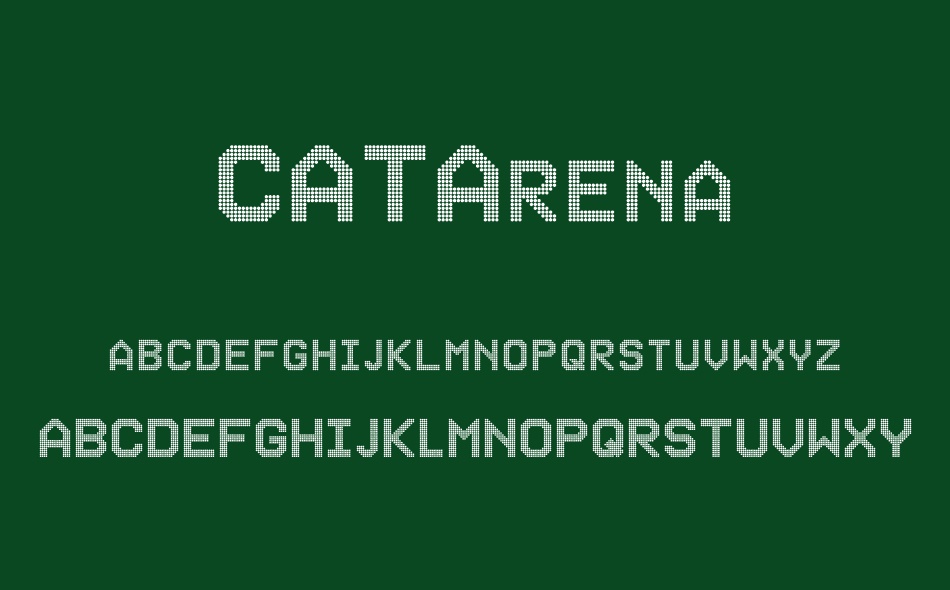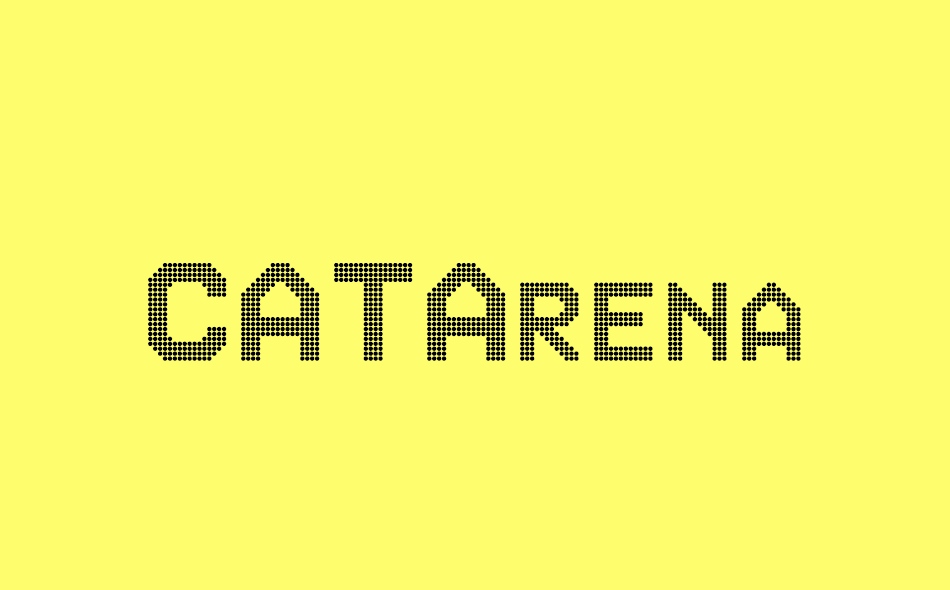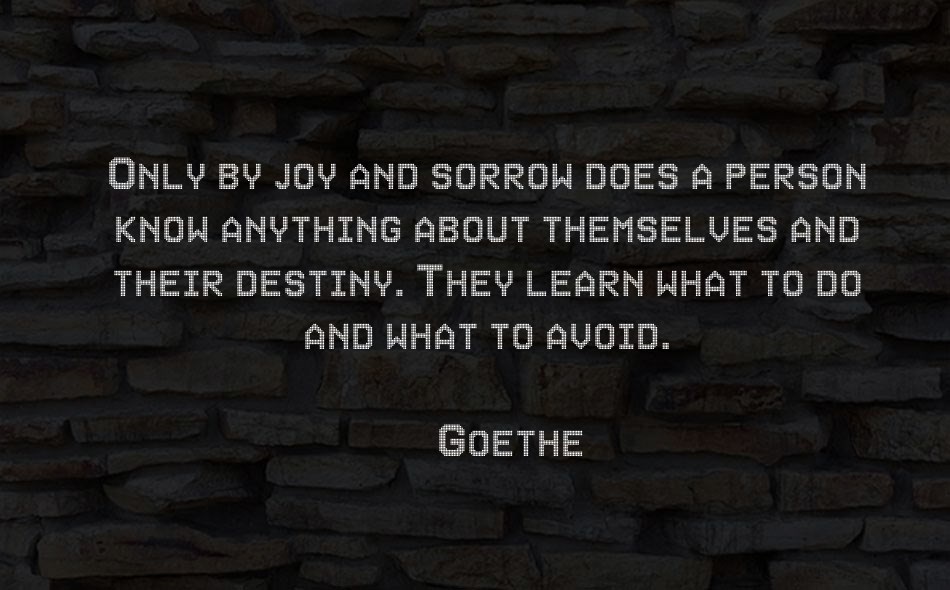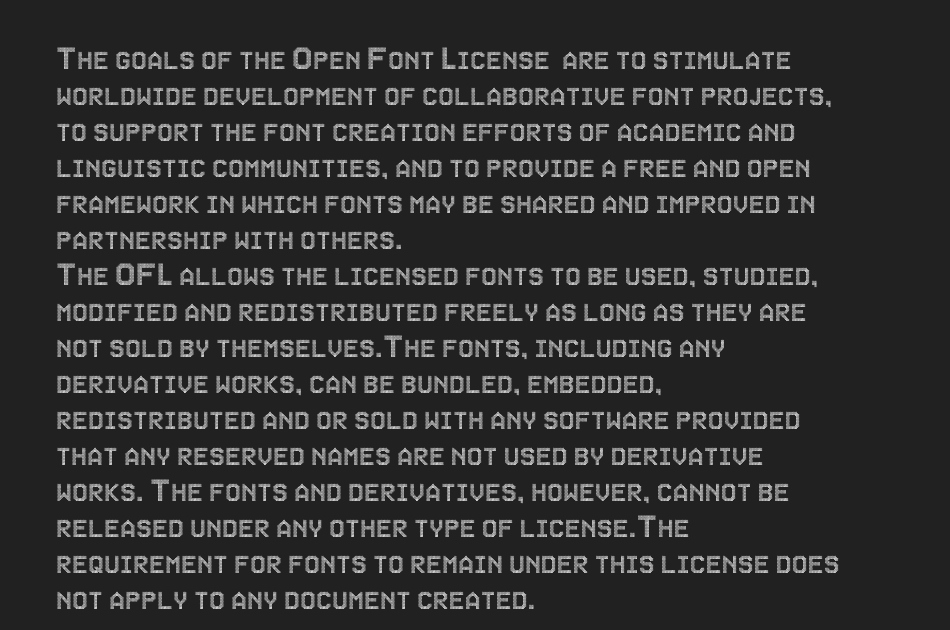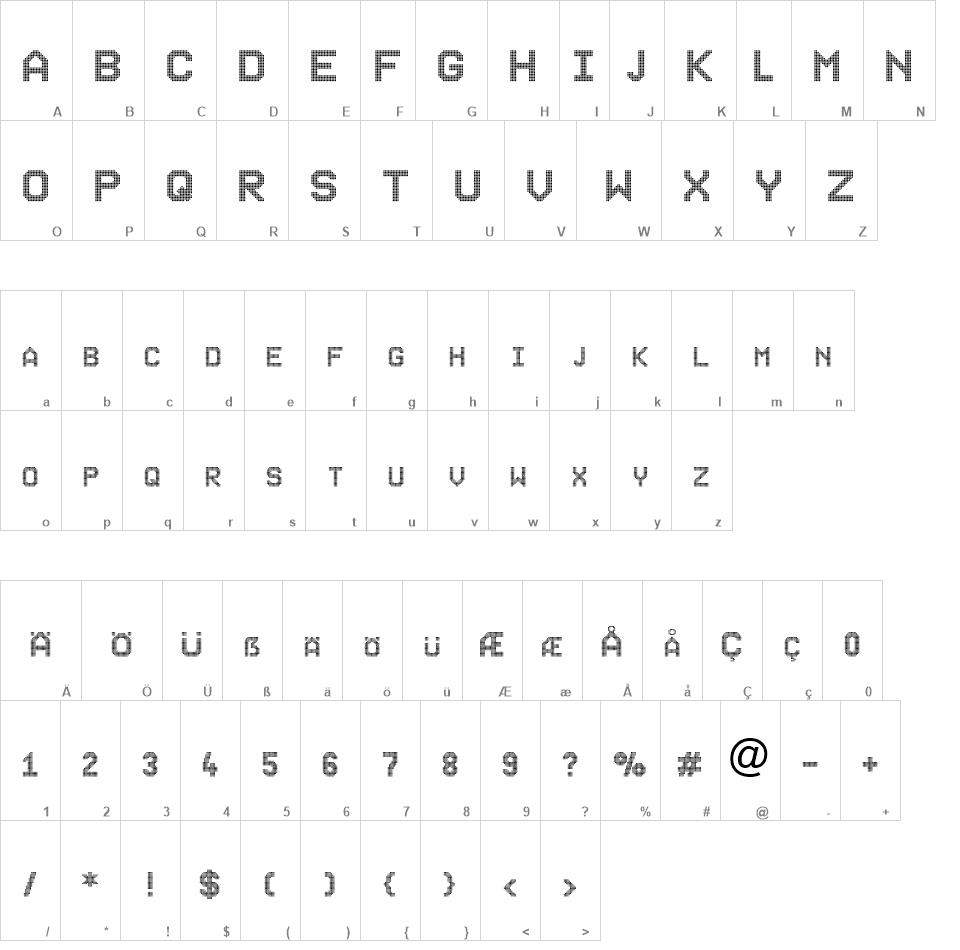
CAT Arena font
September 18, ein Forenmitglied zeigt die Buchstaben einer 1976 installierten Stadionanzeige und fragt nach der dort verwendeten Schrift. Schnell zeigt sich, dass diese damals als reine Digital-Zeichensat-ROM schrift bit fr bit programmiert wurde, und nie als Satzschrift verfgbar war. Da sie so einige interessante Merkmale hat, habe ich dies jetzt nachgeholt.
Untersttzt auch Kyrillisch und Griechisch